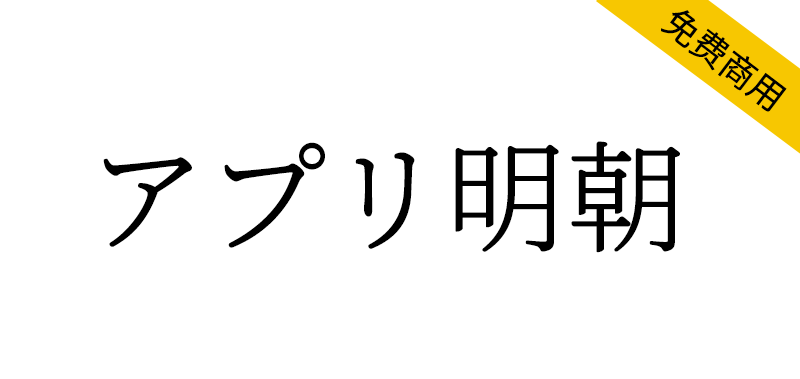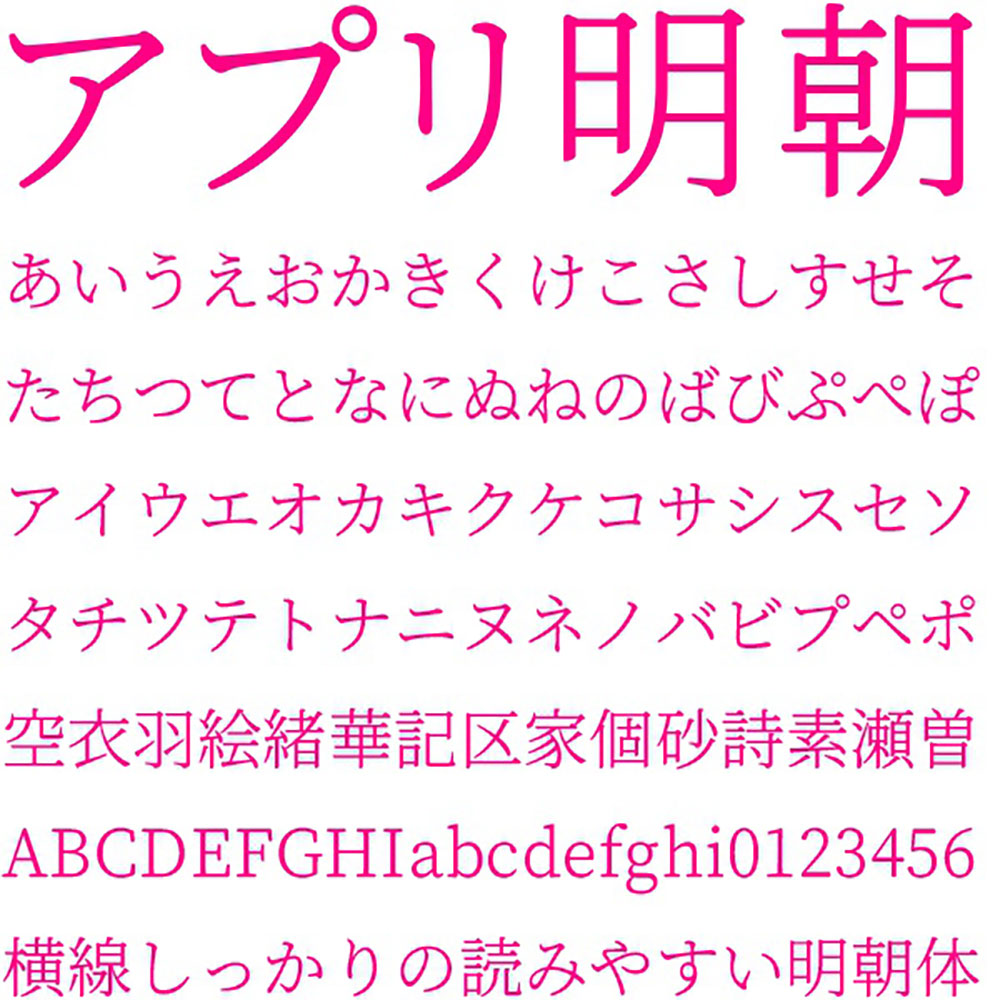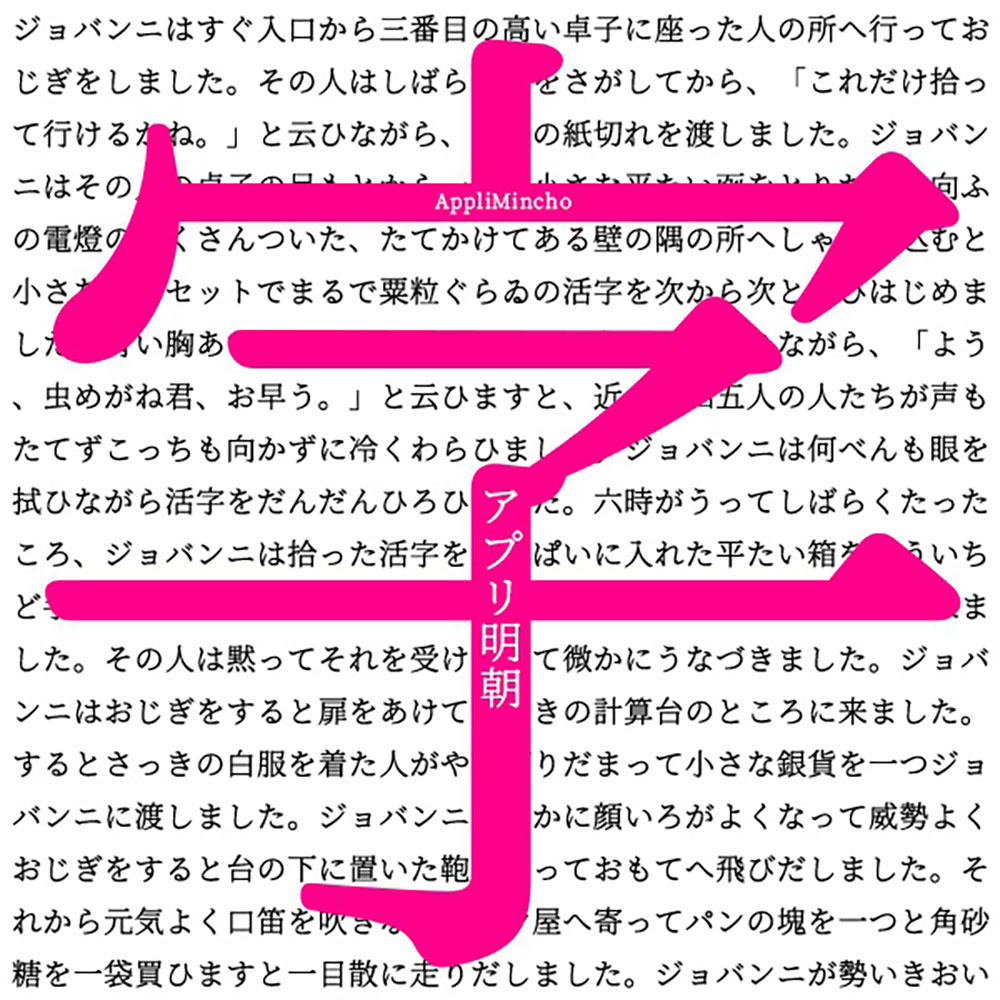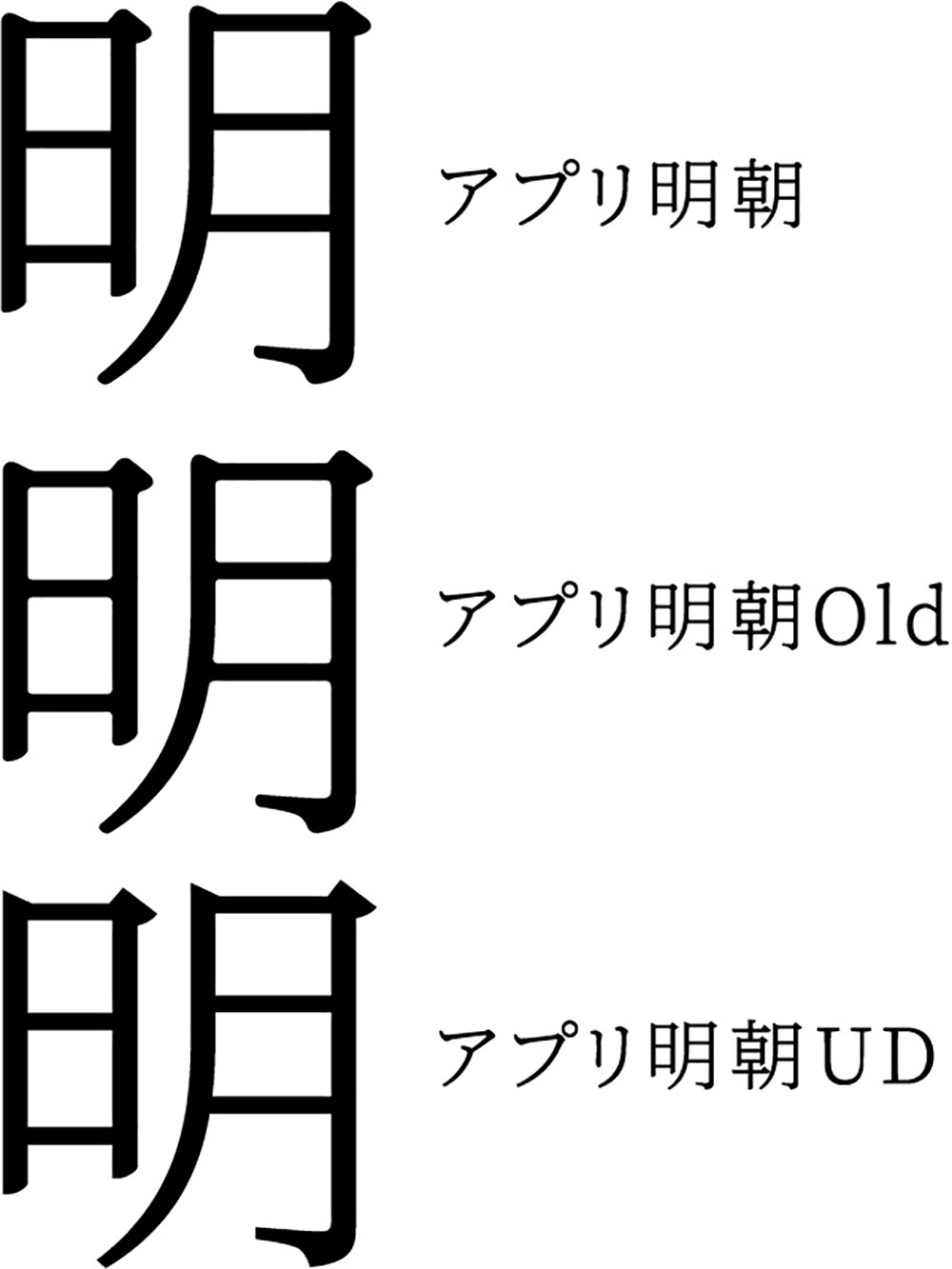
アプリ明朝是一款利用思源宋体的精彩之处的横线稍微粗一点的横太明朝体。与思源宋体相比,横线稍粗,纵线稍细。另外,鳞片、停顿等都更加圆润,不会妨碍视线移动,有助于汉字的自然设计和易读性,具有柔和的氛围,与平假名等形成整体的统一感。
除了アプリ明朝以外,还附带两种字体,在文字上加入渗透,再现墨块的老风味的 “ アプリ明朝Old ” ,鳞片处理锐利的简单的 “ アプリ明朝UD ”。
源ノ明朝の素晴らしさを活かした横線が少し太い横太明朝体です。源ノ明朝と比べると、横線が少し太く、縦線が少し細くなっています。またウロコ、止め等が丸くなって、目の動きの邪魔にならず漢字の自然なデザイン・読みやすさに繋がっていますやわらかい雰囲気で、ひらがな等との全体の統一感があります。
アプリ明朝以外にも2つのフォントを同梱しています。文字に滲みを加え墨だまりを再現したオールド風味の「アプリ明朝Old」ウロコの処理がシャープなままのシンプルな「アプリ明朝UD」